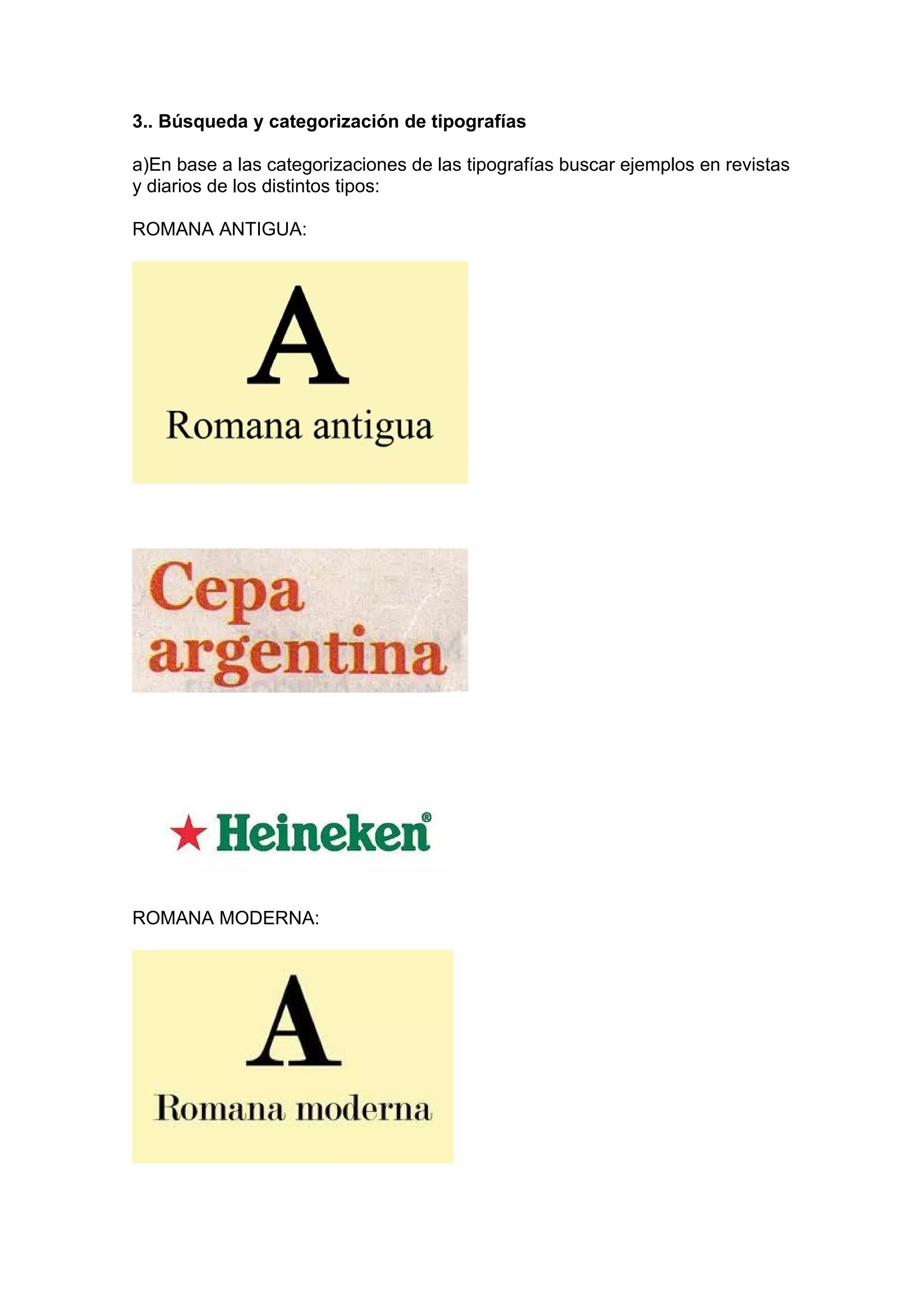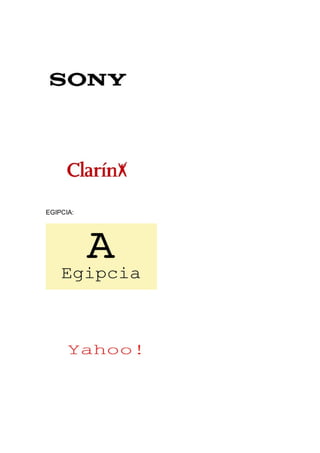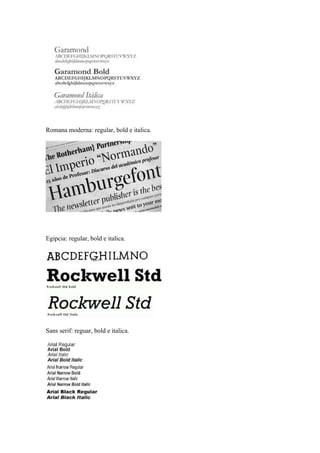
3.. Búsqueda y categorización de tipografías
a)En base a las categorizaciones de las tipografías buscar ejemplos en revistas
y diarios de los distintos tipos:
ROMANA ANTIGUA:
ROMANA MODERNA:
EGIPCIA:
SIN SERIF:
FANTASIA:
b) DE DISTINTAS FAMILIAS TOMAR EJEMPLOS DE VARIABLES:
REGULAR
NEGRITA (BOLD)
CURSIVA (ITÁLICA)
Romana antigua: regular, bold e italica
Romana moderna: regular, bold e italica.
Egipcia: regular, bold e italica.
Sans serif: reguar, bold e italica.
Fantasia: regular, bold e italica.
c) Buscar un ejemplo de composición gráfica (aviso, afiche, postal, tapa de
libro, etc) cuya figura principal sea la tipografía ( sin imagen)
Describir que connotación surge a partir de la tipografía.
Esta es una publicidad grafica de una editorial británica, con experiencia en libros de bolsillo.
Esta campaña de una serie de tres avisos, bajo el eslogan: “Travel with words, meet the world”
(“viaja con palabras y conoce el mundo”).
Denotativamente vemos la palabra “London” con tipografía egipcia con todas sus letras en
mayúscula, pero con la letra “O” en un tamaño mas pequeño y en color negro( a diferencia de
las otras que están en color rojo).
La connotación que surge a través de la tipografía se da en la particularidad que tienen las
letras “O" que nos remiten a un tipico autobus de londres, que acompañado con el eslogan da
entender que leyendo también podemos conocer Londres.